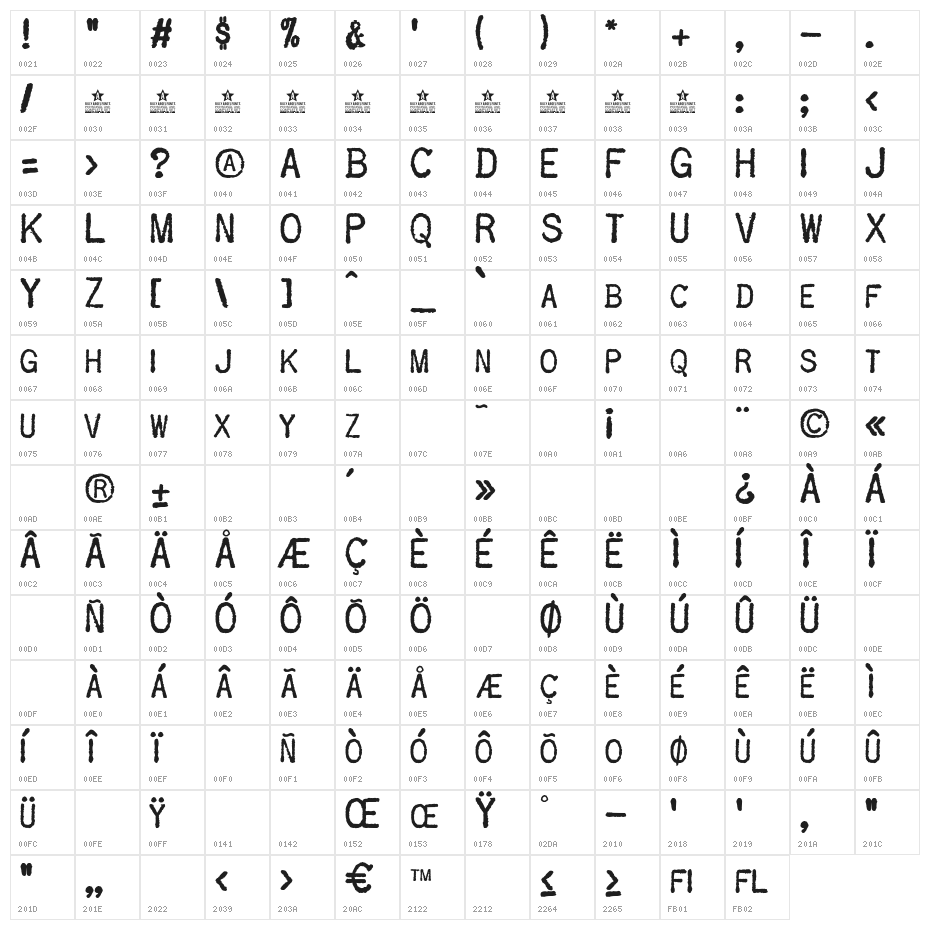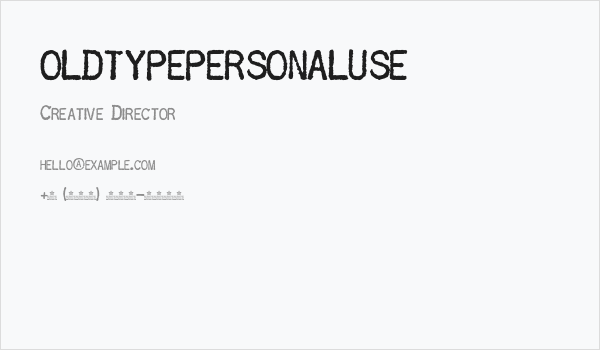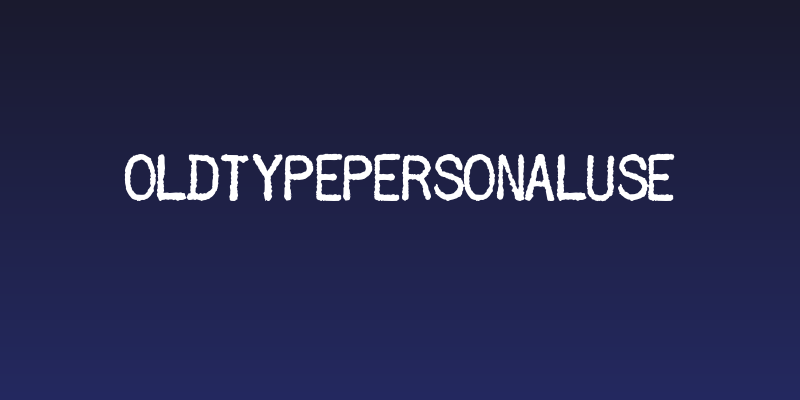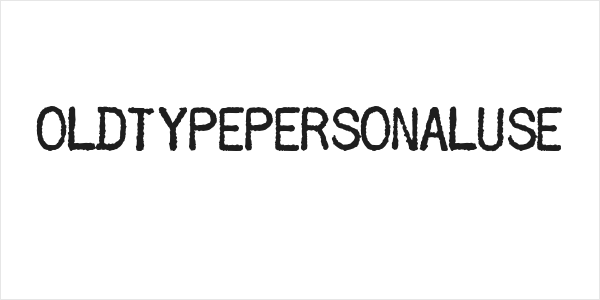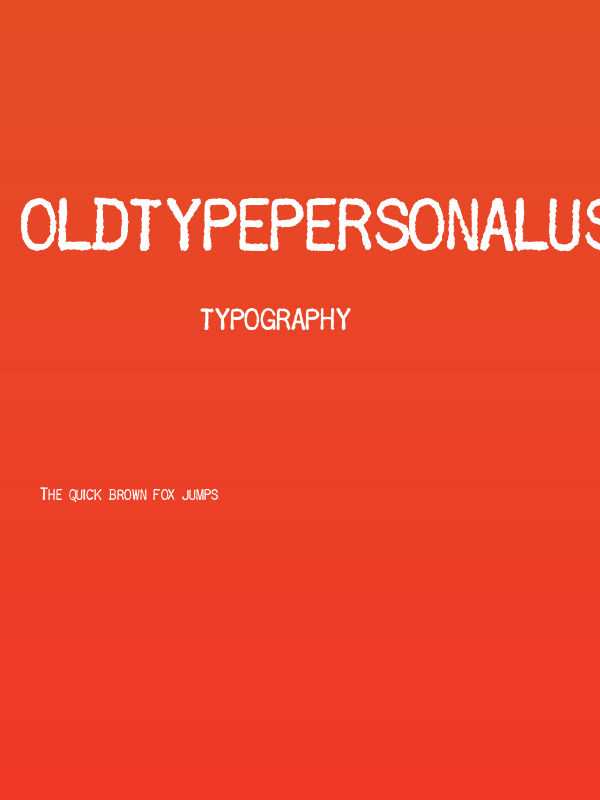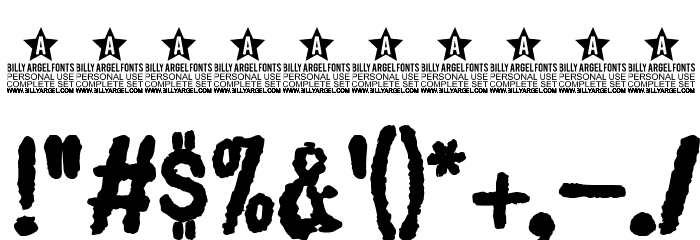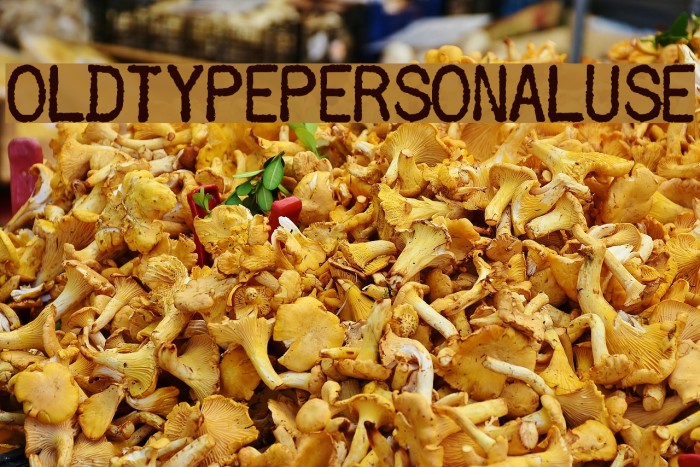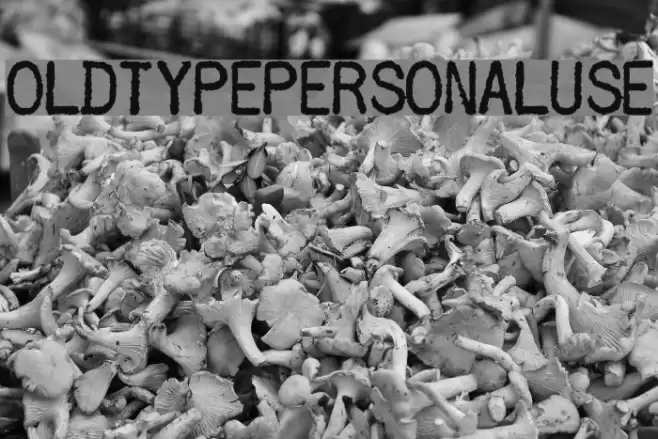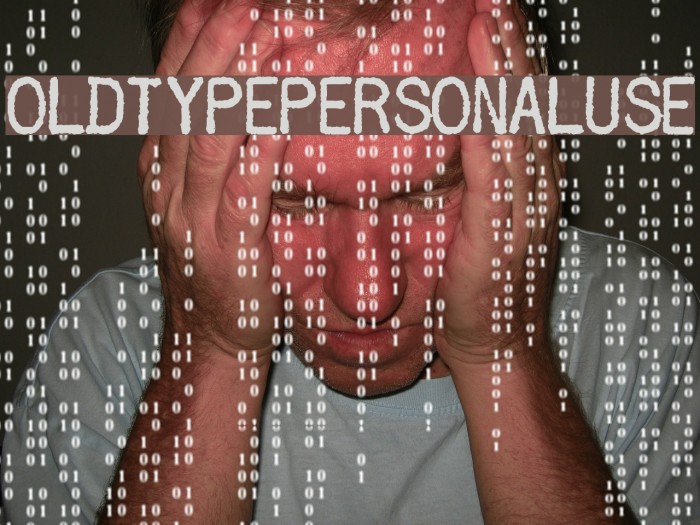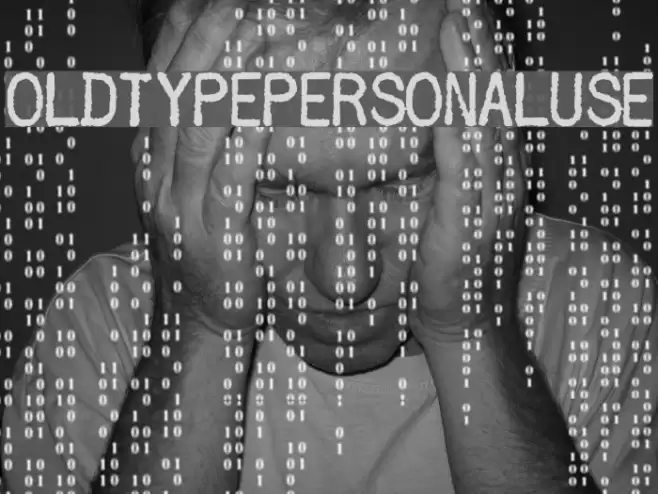
OLDTYPEPERSONALUSE Font
✎ Messy
| الفئات | Messy |
| النمط العام | Vintage, Grunge |
| مشاريع مقترحة | Ideal for posters, album covers, branding for edgy or vintage-themed products, and any design requiring a bold, textured look. |